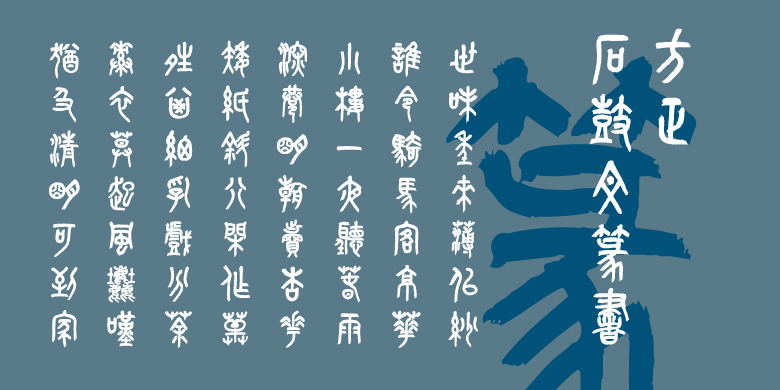
方正石鼓文篆书
常规书写·毛笔
关于石鼓文:
石鼓文是唐代在陕西凤翔发现的我国最早的石刻文字,世称“石刻之祖”。因为文字是刻在十个鼓形的石头上,故称“石鼓文”。内容介绍了战国时期秦国国君游猎时的10首四言诗,亦称“猎碣”。今中国考古界一般认为是战国时代秦国的遗物。石鼓文的字体,上乘西周金文,下启秦代小篆,从书法上看,石鼓文上承《秦公簋》法则,然而更趋于方正丰厚,用笔起止均为藏锋,圆融浑劲,结体促长伸短,匀称适中,古茂雄秀。石鼓文集大篆之成,开小篆之先河,在书法史上起着承前启后的作用。是由大篆向小篆衍变而又尚未定型的过渡性字体。
字体特征:
方正石鼓文篆书是以石鼓文遗存字形的书法特点为基础临创开发的,结体方正匀整,舒展大方,线条饱满圆润,笔意浓厚。